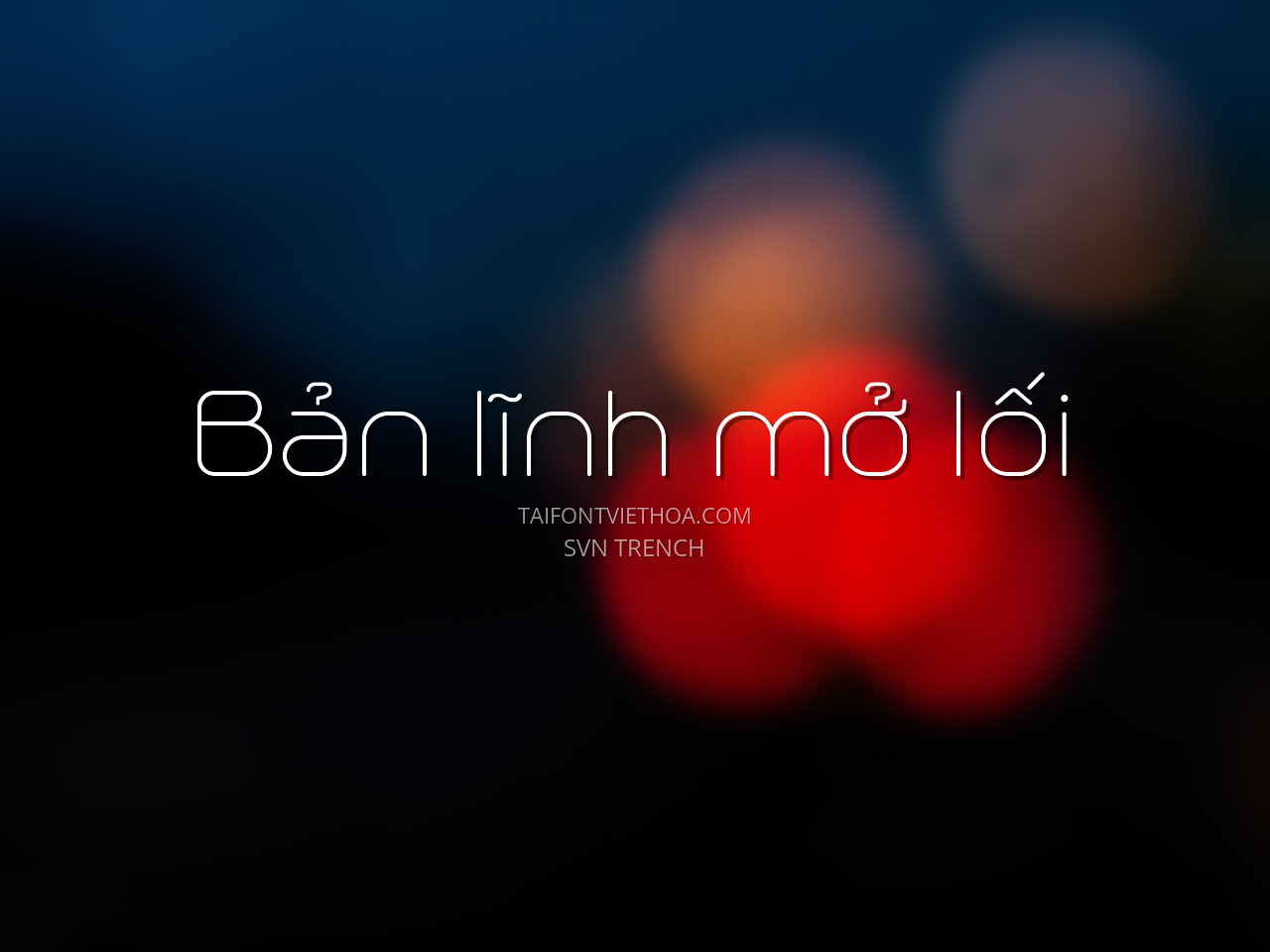
Giới thiệu về Trench – Font sans-serif hiện đại, hình khối mạnh mẽ
Trench (tên gốc: Trench Typeface) là phông chữ sans-serif hiện đại do SimpleType Studios(Anh) thiết kế và phát hành trên các nền tảng quốc tế từ năm 2019. Được lấy cảm hứng từ phong cách hình học tối giản, Trench gây ấn tượng với các đường nét chắc chắn, cân đối và đặc biệt phù hợp với các thiết kế mang tinh thần công nghệ, sáng tạo. Bản gốc hỗ trợ hơn 60 ngôn ngữ Latin, đáp ứng đa dạng nhu cầu thiết kế toàn cầu cho cả bản in và kỹ thuật số.
Phiên bản SVN Trenchđã được STYLEno.1 FontsViệt hóa hoàn thiện, bổ sung đầy đủ dấu tiếng Việt, căn chỉnh kerning và tối ưu hóa hinting để đảm bảo hiển thị sắc nét trên mọi nền tảng thiết kế. Font được taifontviethoa.comtuyển chọn, kiểm thử kỹ càng trên nhiều phần mềm như Adobe Illustrator, Photoshop, Canva…, giúp đảm bảo font không lỗi dấu, không vỡ nét kể cả khi dùng ở kích cỡ lớn hoặc in ấn chuyên nghiệp. SVN Trench Việt hóa phù hợp cho những ai cần một font sans-serif hiện đại, gọn gàng và cá tính cho dự án sáng tạo của mình.
Đặc điểm thiết kế, ứng dụng và ngành nghề phù hợp
Trench thuộc nhóm sans-serif – không chânvới cấu trúc hình học rõ ràng, nét chữ đồng đều, khoảng cách chữ tối ưu cho khả năng đọc ở cả kích thước lớn và nhỏ. Font mang phong cách tối giản, hiện đại, dễ kết hợp với các font khác trong hệ thống nhận diện thương hiệu hoặc thiết kế quảng cáo. Các ký tự số, glyph đặc biệt, cùng với bộ chữ hoa cân đối giúp tăng sự linh hoạt trong trình bày tiêu đề, logo hoặc bảng hiệu.
Ứng dụng tiêu biểu
– Logo & nhận diện:Thương hiệu công nghệ, startup, agency sáng tạo, shop thời trang, digital studio.
– Banner & tiêu đề:Banner website, poster quảng cáo, biển hiệu, brochure.
– Ấn phẩm truyền thông:Ấn phẩm số, standee, flyer, tạp chí kỹ thuật số.
Ngành nghề phù hợp
Trench là lựa chọn lý tưởng cho ngành công nghệ, quảng cáo, sáng tạo, thời trang, digital agency, sự kiện, gaming… Khi kết hợp cùng font serif hoặc script, Trench giúp tổng thể thiết kế hài hòa, cá tính và chuyên nghiệp hơn. Tải ngay phiên bản Việt hóa tại taifontviethoa.com để trải nghiệm trọn bộ glyph miễn phí cho mọi dự án của bạn.